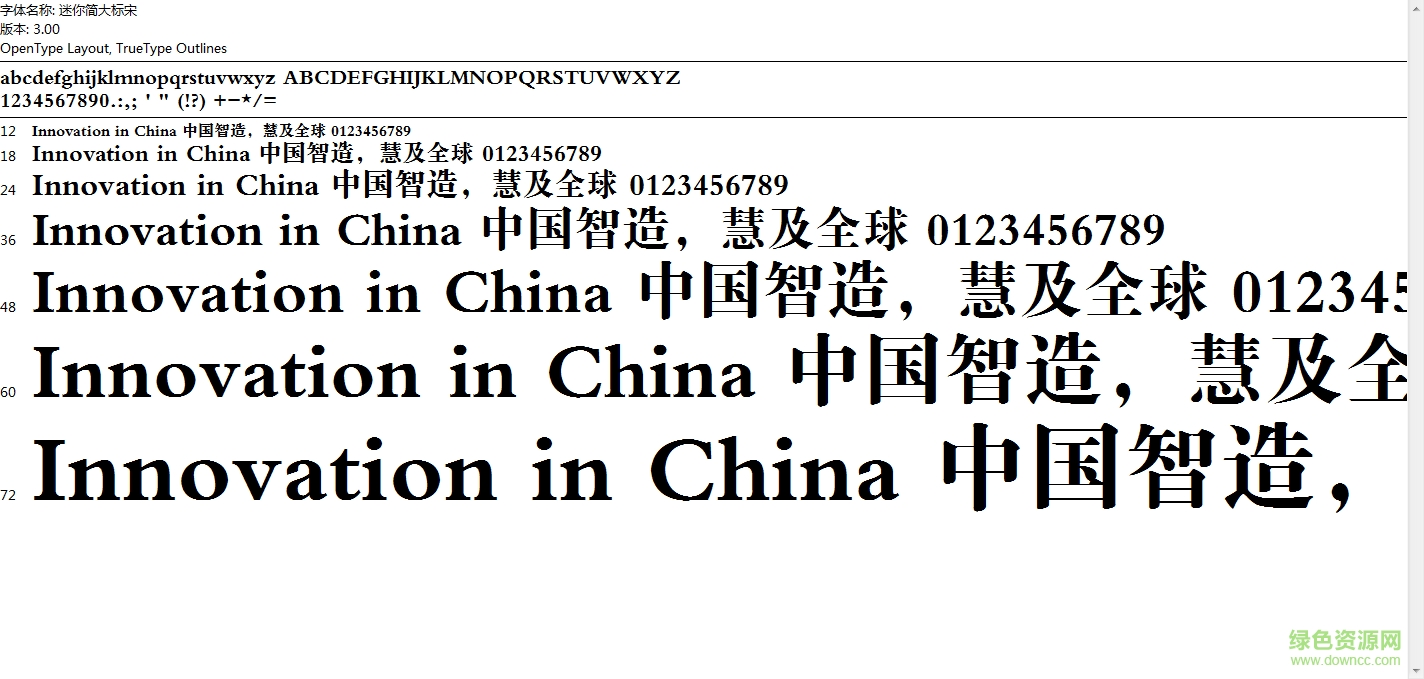
迷你簡(jiǎn)大標(biāo)宋常規(guī)是一款端莊大氣的簡(jiǎn)體字體,端莊大氣、清新淡雅、華美自然等特點(diǎn),整體形象相當(dāng)不錯(cuò),可應(yīng)用于設(shè)計(jì)、排版、說(shuō)明書(shū)、新聞等方面,喜歡的朋友歡迎來(lái)綠色資源網(wǎng)下載!